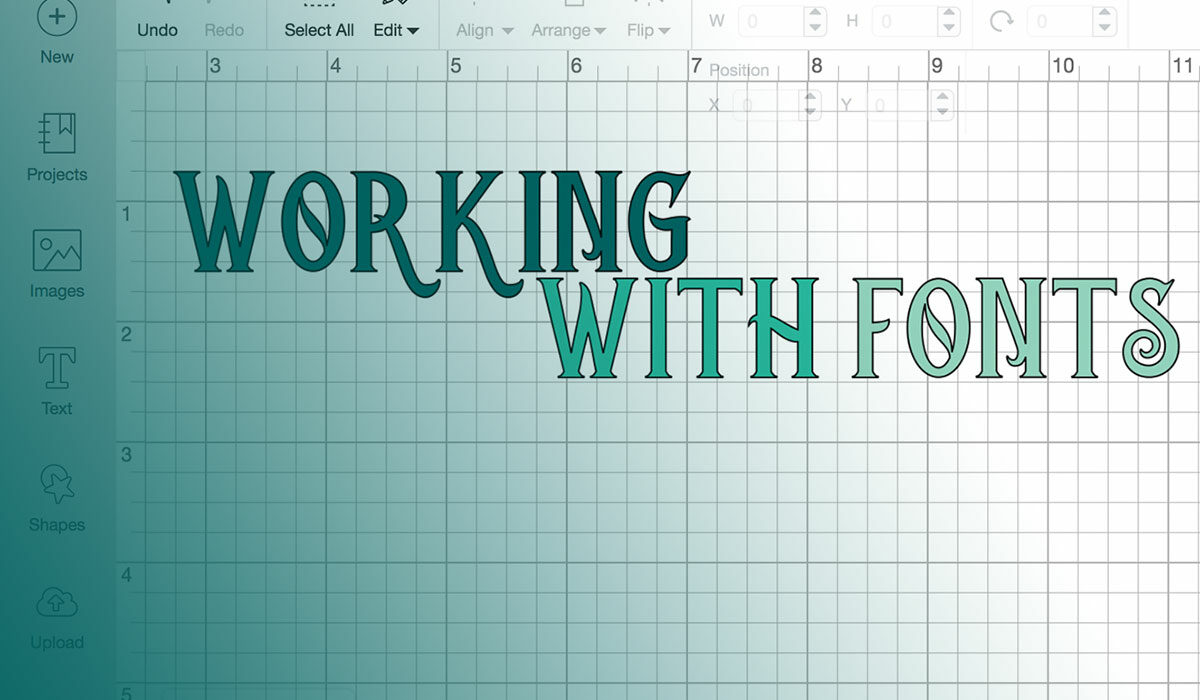
Haben Sie jemals das Verlangen gespürt, alles um Sie herum zu personalisieren? Das ist die Magie der Kreativität, die darauf wartet, freigesetzt zu werden, besonders wenn Sie ein Werkzeug wie Cricut Design Space zur Verfügung haben.
Heute tauchen wir in einen echten Gamechanger für Ihre Designs ein: wie man Schriftarten zu Cricut Design Space hinzufügt.
Es geht nicht nur darum, Ihr Design-Toolkit zu erweitern – es geht darum, eine Welt zu erschließen, in der Ihr Text tanzen, schreien, flüstern oder was auch immer Sie möchten, tun kann.
In den folgenden Zeilen bereiten Sie sich darauf vor, Ihren Ansatz zum Handwerk und zur Projektgestaltung zu transformieren.
Sie lernen nicht nur die Grundlagen des Hochladens von Schriftarten, sondern auch die Feinheiten der Auswahl der richtigen Schriftarten, die Schönheit und Funktionalität vereinen.
Von der Suche nach kostenlosen und kostenpflichtigen Schriftarten mit den entsprechenden Lizenzen bis hin zur Sicherstellung, dass sie so sauber geschnitten werden, wie sie auf Ihrem Bildschirm erscheinen.
Sie werden von einem Schriftart-Neuling zu einem klügeren, selbstbewussteren Designer avancieren.
Wie man Schriftarten zu Cricut Design Space hinzufügt: Schneller Workflow
Hier sind die Schritte zum Hinzufügen von Schriftarten zu Cricut Design Space:
- Laden Sie die Schriftart herunter, die Sie verwenden möchten, und entpacken Sie die Datei, falls erforderlich.
- Installieren Sie die Schriftart auf Ihrem Computer. Unter Windows klicken Sie mit der rechten Maustaste auf die Schriftartdatei und wählen „Installieren“. Auf einem Mac öffnen Sie das Font Book und ziehen die Schriftartdatei hinein.
- Starten Sie Cricut Design Space vollständig neu. Unter Windows schließen Sie alle Design Space-Fenster. Auf einem Mac gehen Sie zum Design Space-Menü und wählen „Beenden“. Dies ist ein entscheidender Schritt, damit Design Space die neue Schriftart erkennt.
- Öffnen Sie ein neues Projekt in Design Space und klicken Sie auf das „Text“-Symbol, um Text zur Leinwand hinzuzufügen.
- Klicken Sie auf das Schriftartenmenü oben und Sie sehen zwei Registerkarten – „Cricut“, die Schriftarten aus ihrer Bibliothek zeigt, und „System“, die installierte Schriftarten auf Ihrem Computer zeigt.
- Klicken Sie auf die Registerkarte „System“ und geben Sie ein paar Buchstaben des Namens Ihrer neuen Schriftart in das Suchfeld ein. Ihre installierte Schriftart sollte in der Liste erscheinen.
- Klicken Sie auf Ihre neue Schriftart, um sie auszuwählen, und sie wird auf den Text auf Ihrer Leinwand angewendet.
Das war’s! Die Schriftart ist jetzt verfügbar, um sie in Ihren Cricut-Projekten zu verwenden. Denken Sie daran, Design Space immer neu zu starten, nachdem Sie eine neue Schriftart installiert haben, damit sie richtig angezeigt wird.
Schriftarten zur Hochladung finden
Kostenlose Schriftarten
Stellen Sie sich eine Schatztruhe vor, aber anstelle von Gold ist sie prall gefüllt mit stilvollen, skurrilen und ausdrucksstarken Schriftarten.
Das ist das Gefühl des Internets, wenn Sie auf der Suche nach der perfekten Ergänzung für Ihr Bastelarsenal sind. Websites wie Google Fonts und Dafont.com sind wie Inseln voller Gratisartikel. Aber hier ist der Haken: Nicht alles, was glänzt, ist Gold.
Andere sind für die kommerzielle Nutzung frei, perfekt, wenn Sie ein Logo für ein lokales Café entwerfen.
Kostenpflichtige Schriftarten
Nun, wenn Sie bereit sind, ein bisschen Geld für das Nonplusultra der Typografie auszugeben, sind Plattformen wie Font Bundles oder Creative Fabrica Ihre Anlaufstellen.
Warum Geld ausgeben? Denken Sie an das polierte Aussehen professioneller Schriftarten und die klare Lizenzierung – sie sagen Ihnen direkt, ob Sie Ihre Designs monetarisieren dürfen. Keine Ratespiele mehr darüber, ob Sie diese entzückenden Urlaubskarten verkaufen können.
Eigenschaften von Schriftarten für Cricut Design Space
Schneidbare Schriftarten
Dabei geht es nicht nur darum, auf dem Bildschirm gut auszusehen. Wenn Sie Ihr Design an eine Cricut-Maschine senden, muss die Schriftart so glatt wie Butter geschnitten werden.
Wählen Sie Schriftarten mit glatten Kanten. Texturierte Kanten könnten Ihnen auf dem Bildschirm einen rustikalen Eindruck vermitteln, aber in der physischen Welt können sie sich in ein Schneide-Albtraum verwandeln!
Halten Sie Ausschau nach diesen Cricut-freundlichen Optionen.